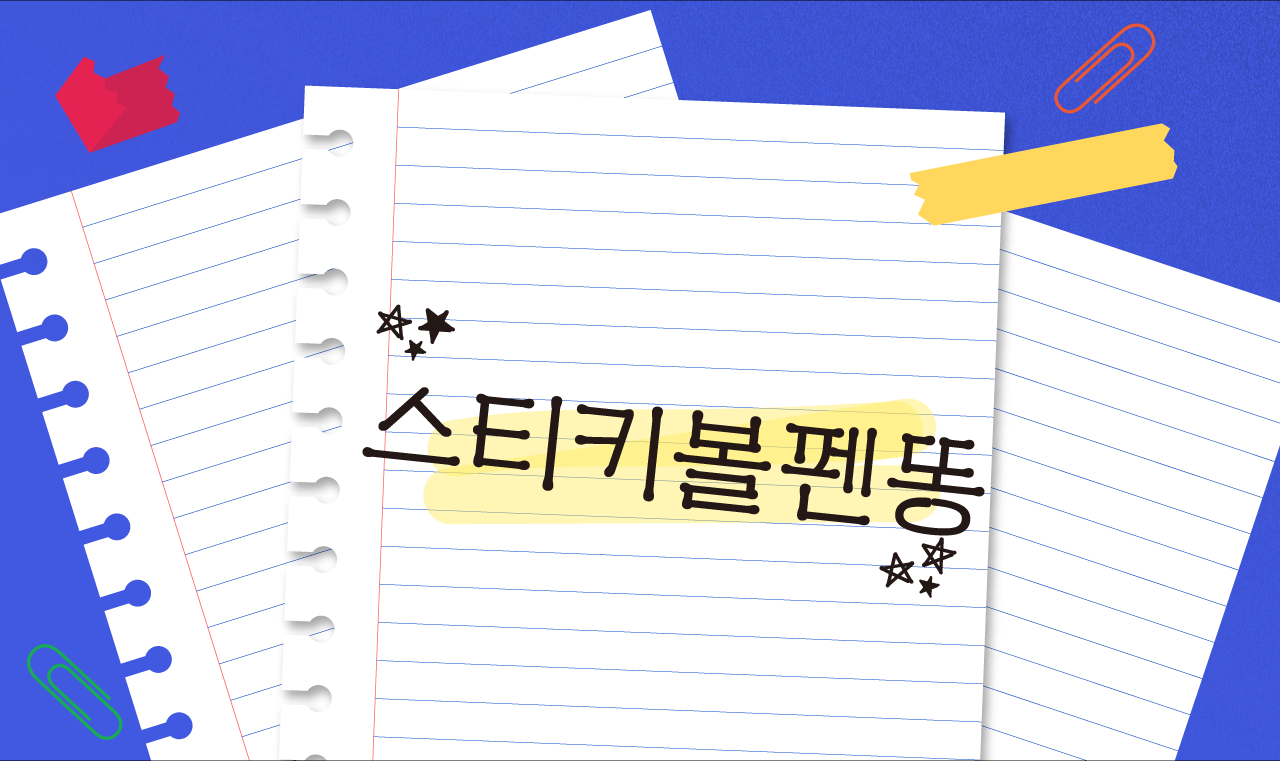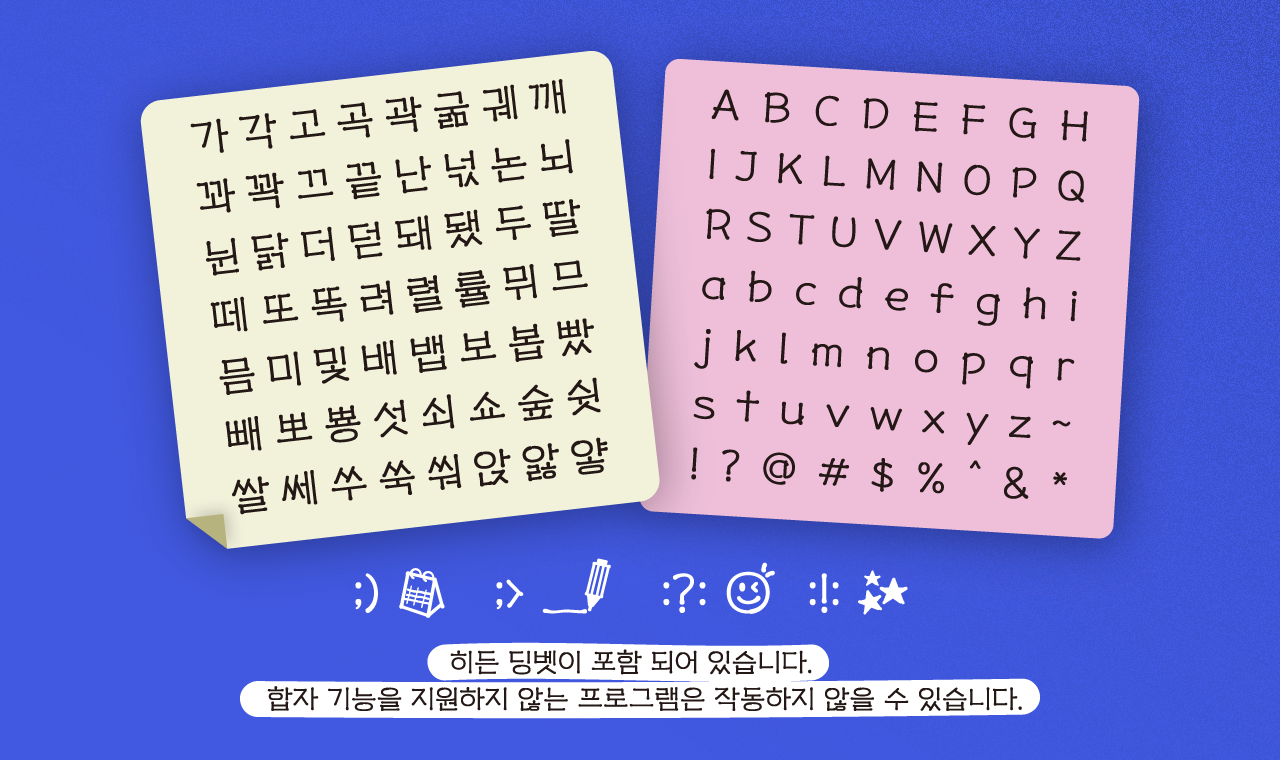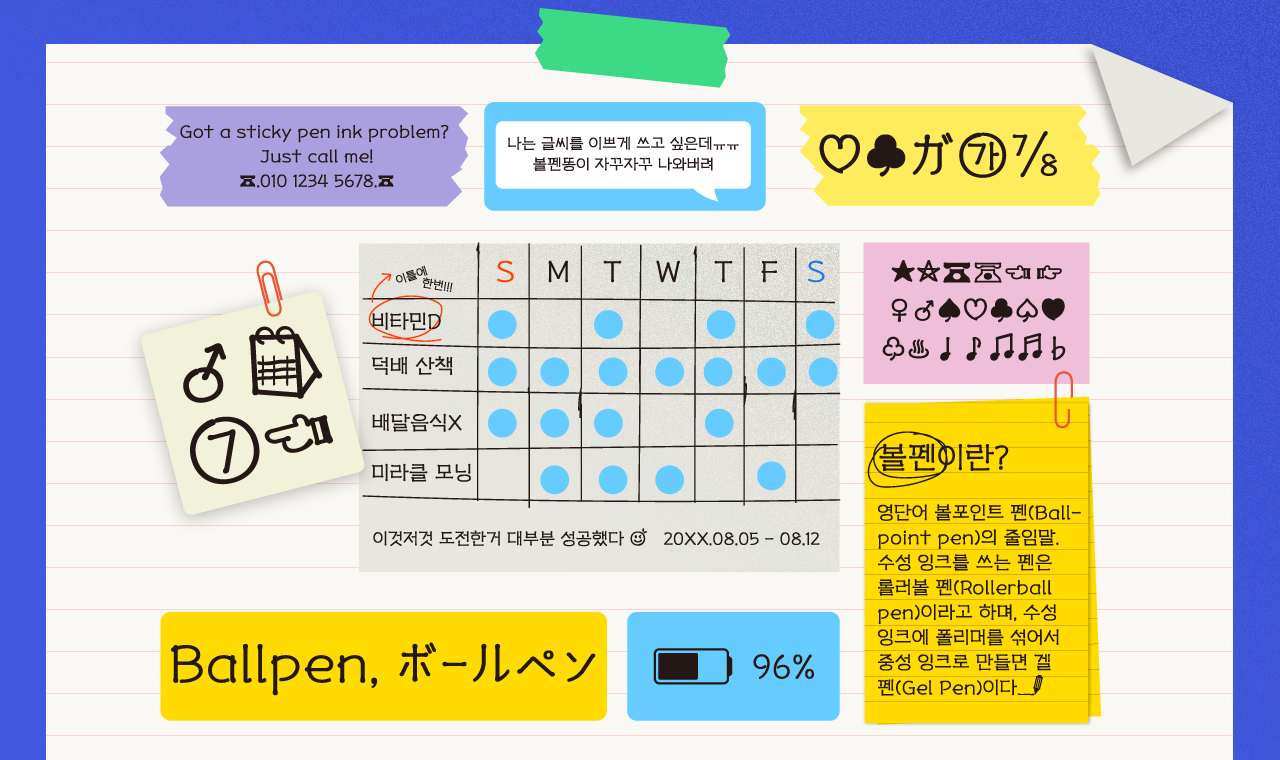
[손글씨]
스티키볼펜똥
Yoon 스티키볼펜똥
스티키볼펜똥은 또박또박 눌러 쓴 단정한 필기체 구조 위에, 볼펜 잉크가 뭉친 듯한 표현을 한 서체입니다. 정제된 형태 속에서도 잔잔한 잉크의 질감이 살아 있어 안정적인 가독성과 함께 손글씨 특유의 자연스러움과 생동감을 전합니다. 일상의 필기에서 느껴지는 따뜻한 감성을 조형적으로 담아내었습니다.